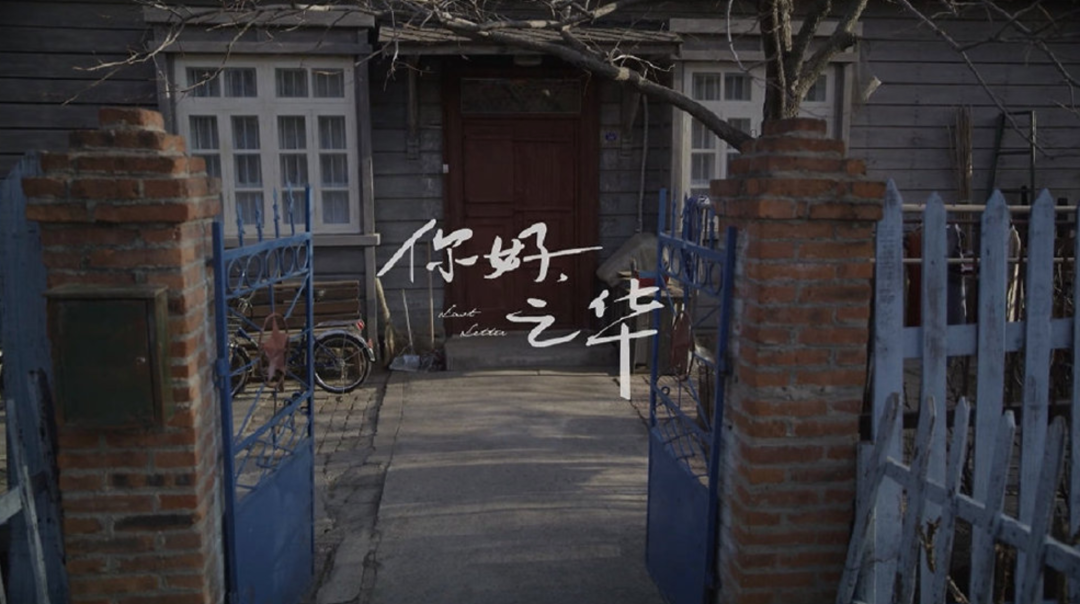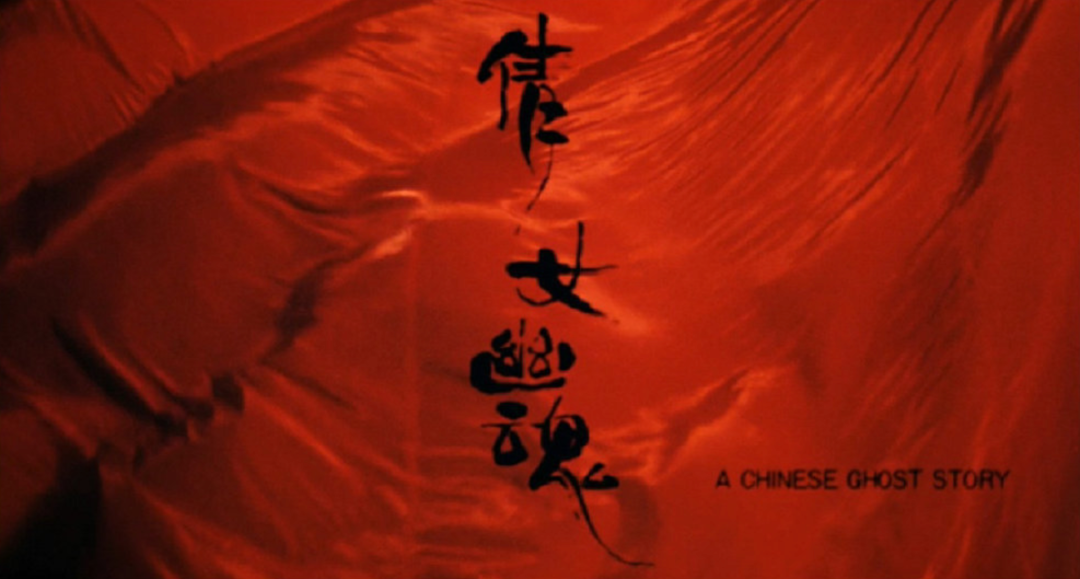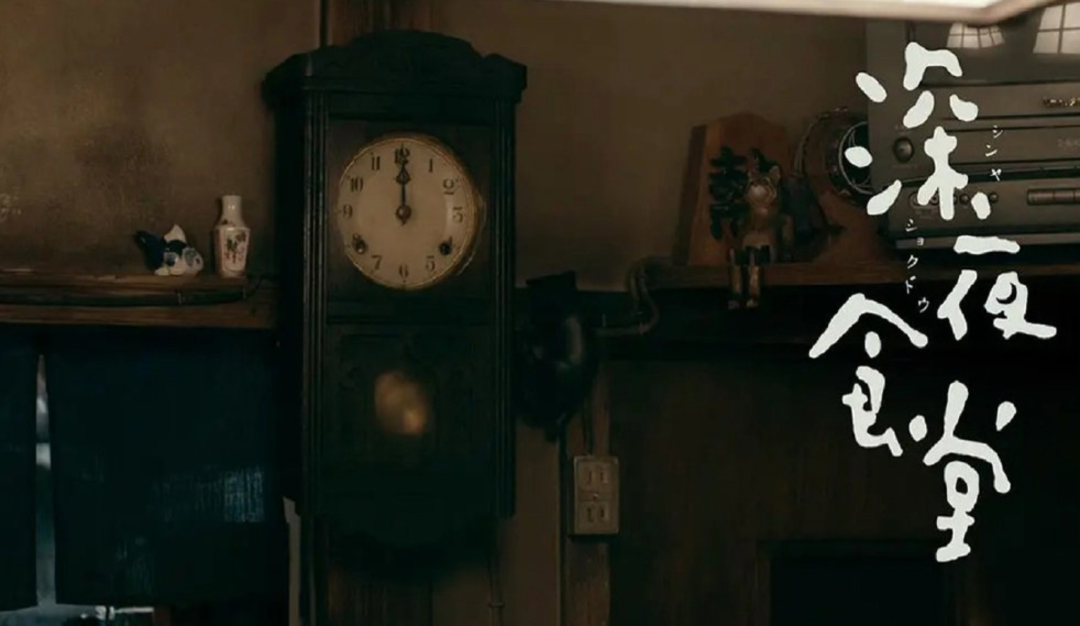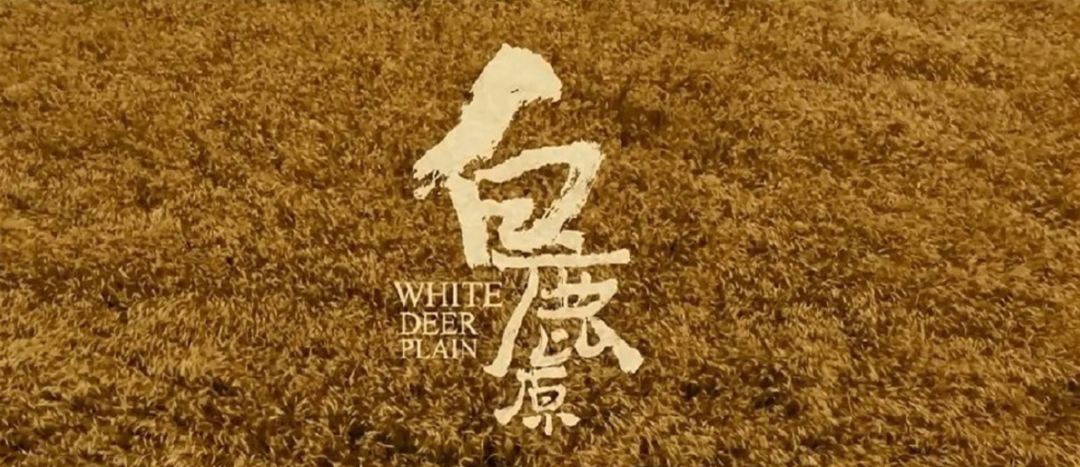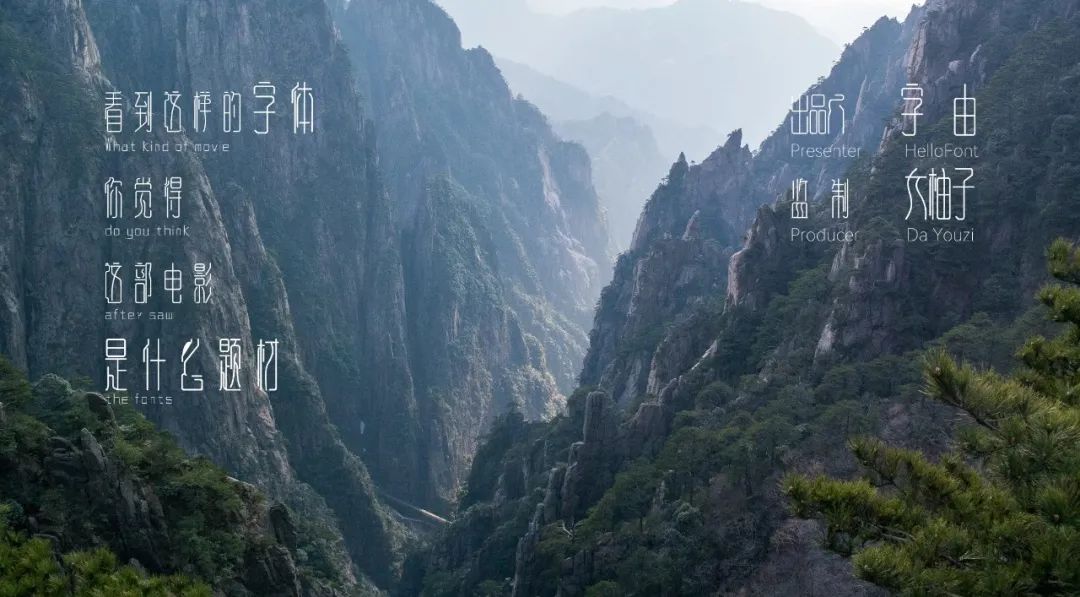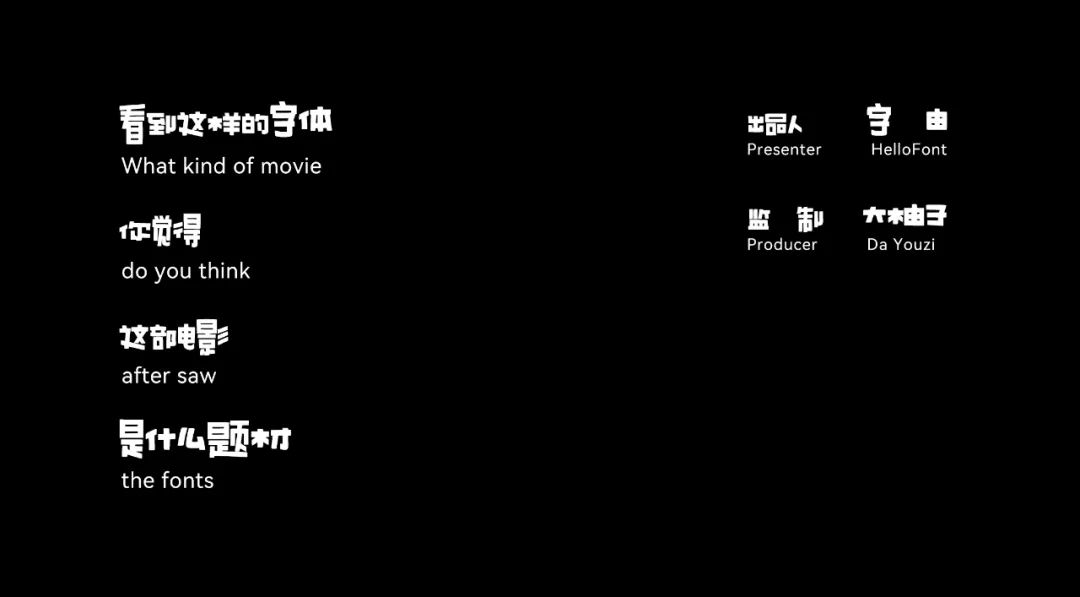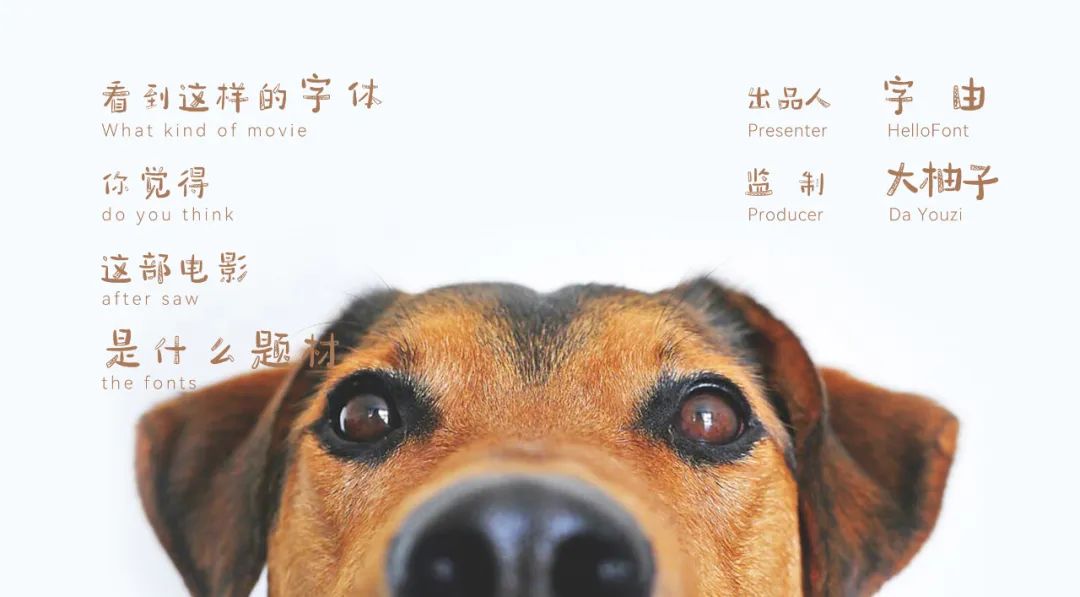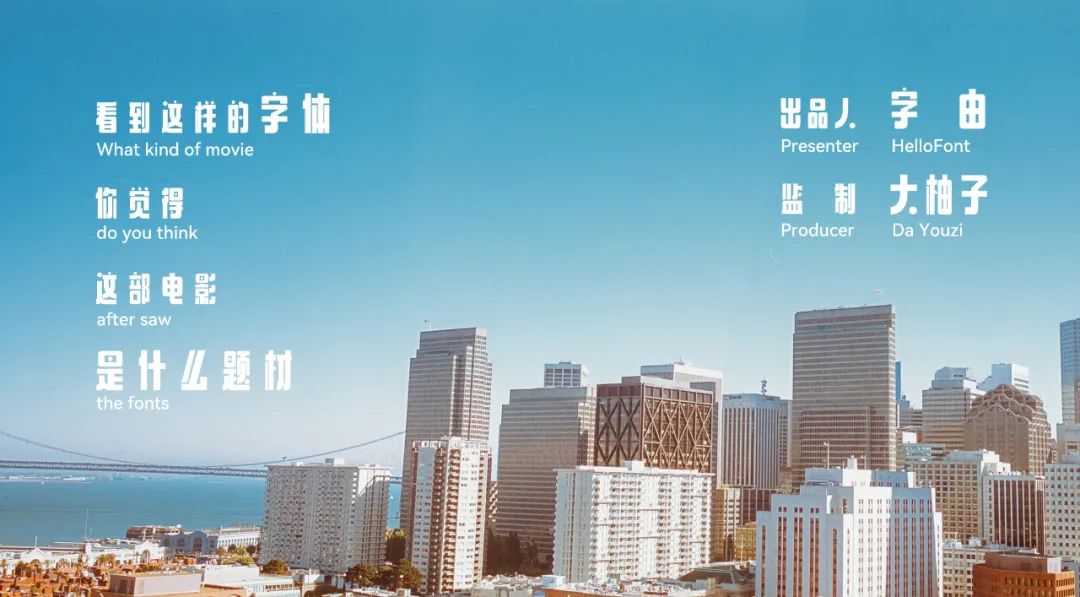
只需一个字体,就能脑补出一部电影,神了!
相信小伙伴们经常看电影,但是你了解电影字体吗?
不同的字体有不同的性格,看到这些字体就好像已经知道了这部影片的内容
比如下面这些~
小伙伴们可能会说,这些都是专门针对电影设计过的字体,当然有内味儿了
🤔有道理,那柚子再拿字由客户端的字体试试~看看没有经过针对性设计的字体到底是什么“性格”
逐浪古禅素食楷体一出手,柚子已经脑补出仙侠世界三生三世的恩怨情仇了👌
百家造字蒲蒲POP妥妥的喜剧风格,柚子已经准备开始笑了🌈
如果是暖暖的宠物题材,点字童稚体可太合适了~
没想到点字稻草人可以完全驾驭住惊悚悬疑,有点细思极恐的感觉了😨
看到字由芳华体就想到上海,这一看就是上海爱情故事,甚至还能看出来是柚子喜欢的Happy Ending❤️
这一看就是文艺片,柚子还脑补出大概内容是去大山里支教😊模仿手写字体,字家童颜体有一手的~
点字机械体,是科幻题材永远的代言人!